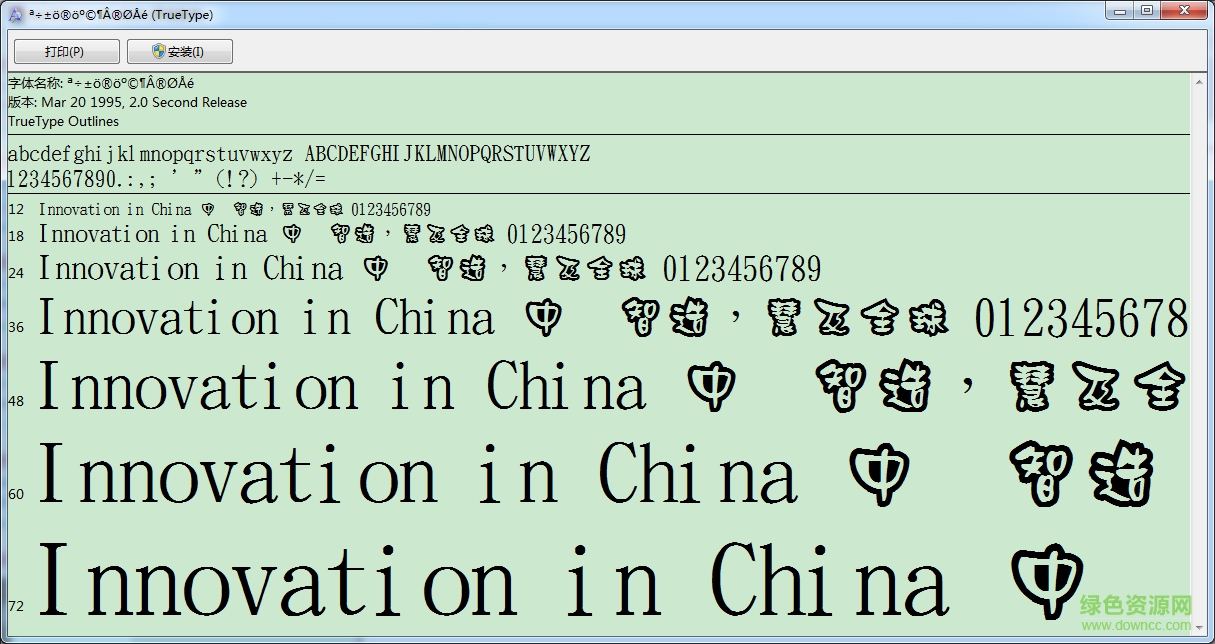
金梅浪漫黑框體字體如同它的名字一樣就是在文字邊緣加上了一層黑框??雌饋砗茏匀唬@類字體也多用于設計一些醒目的廣告標題使用!喜歡這款字體的朋友可以來綠色資源網(wǎng)下載吧!
金梅浪漫黑框體是一款獨具特色的字體,這款字體帶有黑邊框,整體效果看起來非常的漂亮,比較適用于平面設計、廣告設計、報紙雜志等領域。